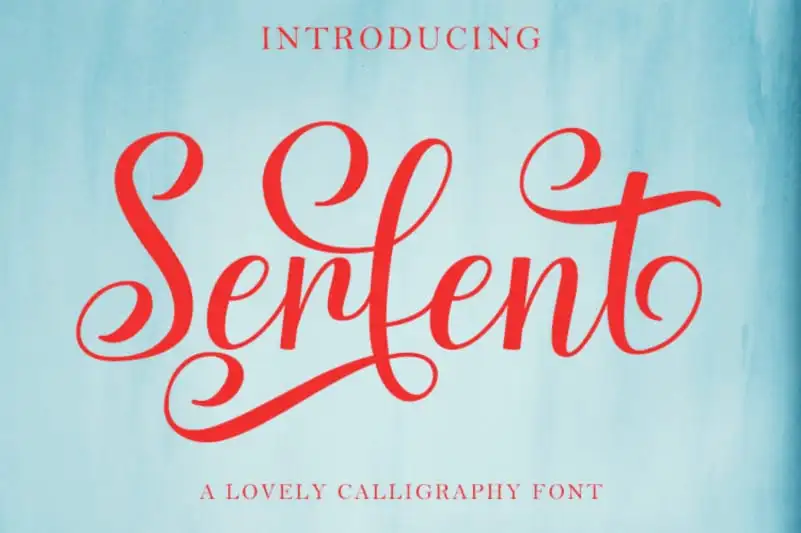
Serfent Script Font – Download Grátis
Serfent Script Font é uma fonte escrita à mão que destaca sua natureza distintiva, suave e eterna. Embora não seja exatamente feita para reproduzir a autêntica letra de um artesão, Serfent captura o espírito delicado e vibrante do processo manual. Essa fonte é uma escolha perfeita para adicionar um toque pessoal aos seus projetos gráficos, seja em cartões de casamento ou agradecimentos, frases inspiradoras em cards de boas-vindas, logotipos ou cartões de negócios. Suas linhas onduladas e as perfeitas curvas do tipo dão um toque único e sofisticado à qualquer design que precise de um toque criativo e autêntico. Serfent Script é uma ótima opção para designers buscando adicionar a sua marca de maneira única, sem perder o charme de uma fonte escrita à mão.